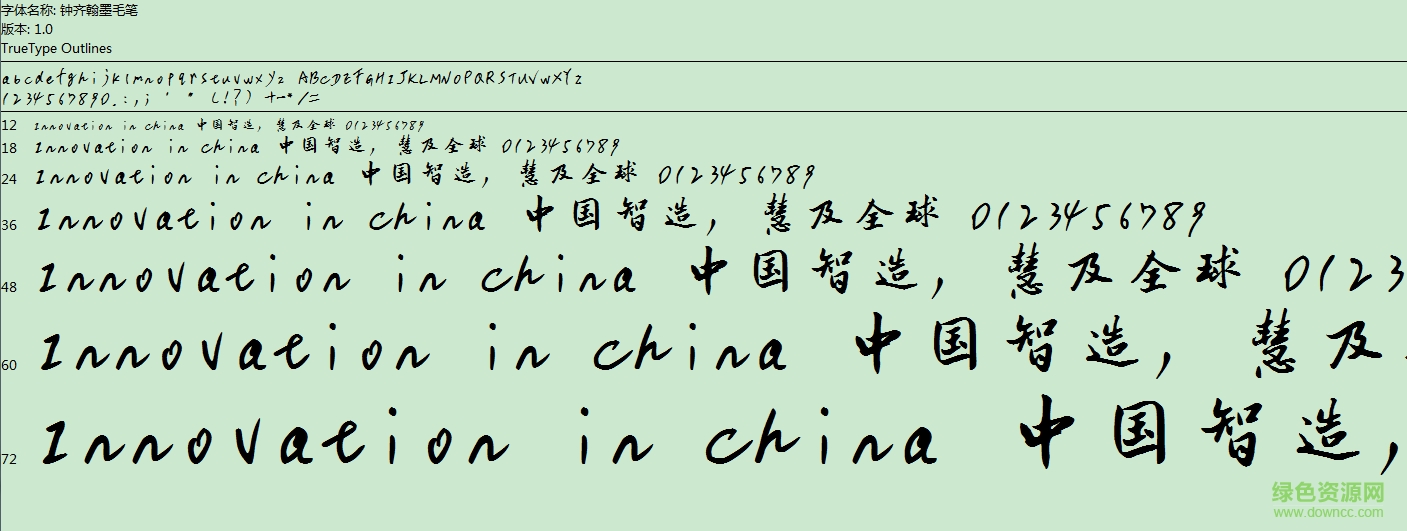
鐘齊翰墨毛筆
鐘齊翰墨毛筆是一款非常漂亮的毛筆書法字體,這款字體瀟灑飄逸,非常適用于毛筆書法設(shè)計方面,以及個人書法練筆,書法愛好者們快來下載體驗一番吧!
鐘齊翰墨毛筆字體介紹
鐘齊翰墨毛筆是一款用于書法方面的字體,字如其人,從某種程度上來說字的好壞可以體現(xiàn)一個人的修養(yǎng)與氣質(zhì),所以練得一手好字還是相當重要的。